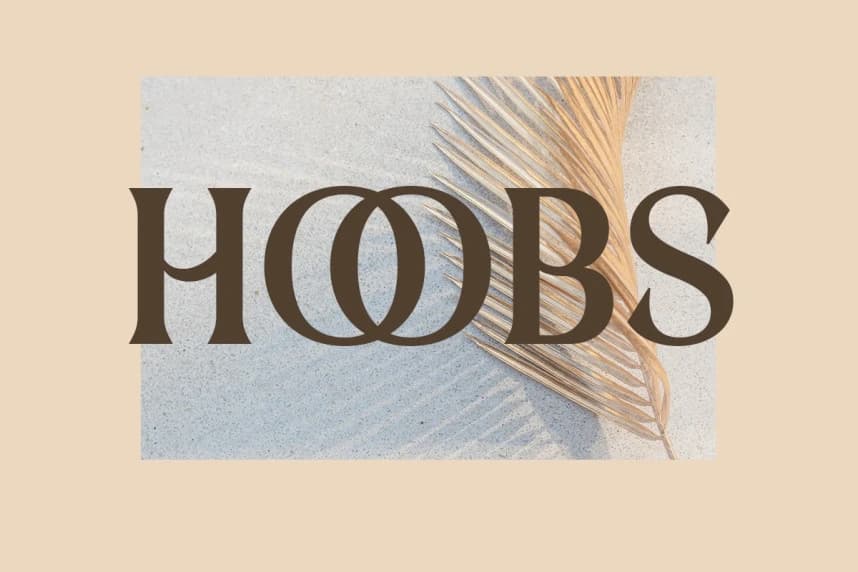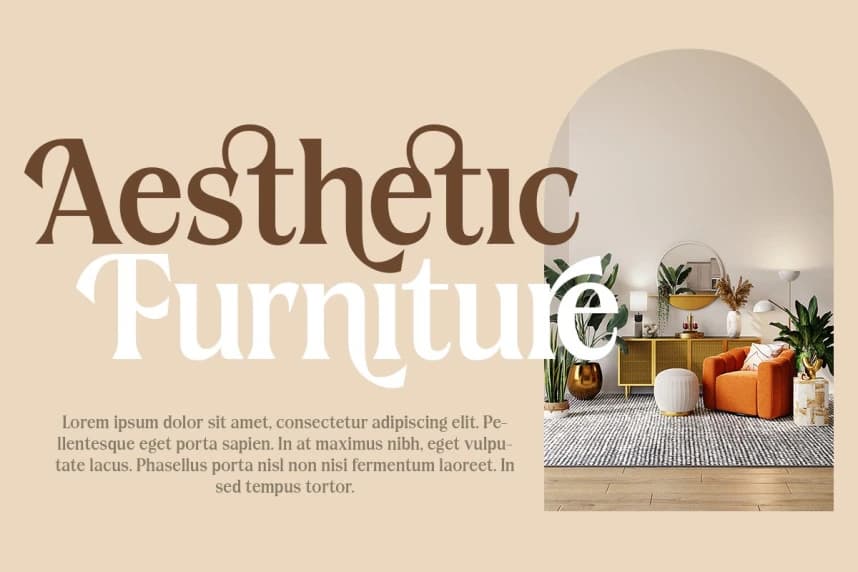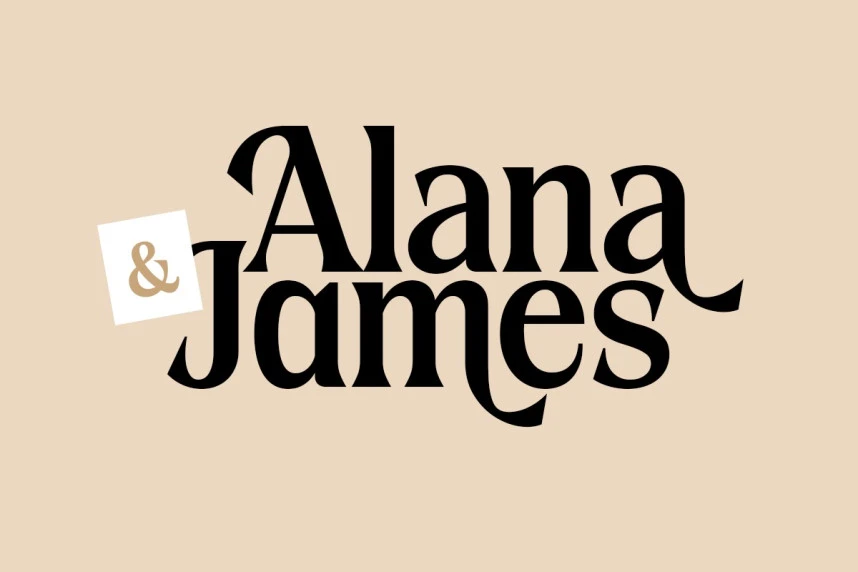
Darena Font
Darena Font - Modern Serif Font Jasmine Classy Serif Font, görünen herkese sade ve zarif bir izlenim sunmak üzere tasarlandı. Bu, her harfin gereksiz süslerden arındırılmış çok temiz bir karaktere sahip olmasıyla uyumludur.
Darena Font - Modern Serif Font Jasmine Classy Serif Font sade ve zarif bir izlenim sunmak amacıyla tasarlanmıştır. Bu durum, her harfte gereksiz süslerden arındırılmış ve çok temiz görünen harflerin karakteriyle uyumludur.